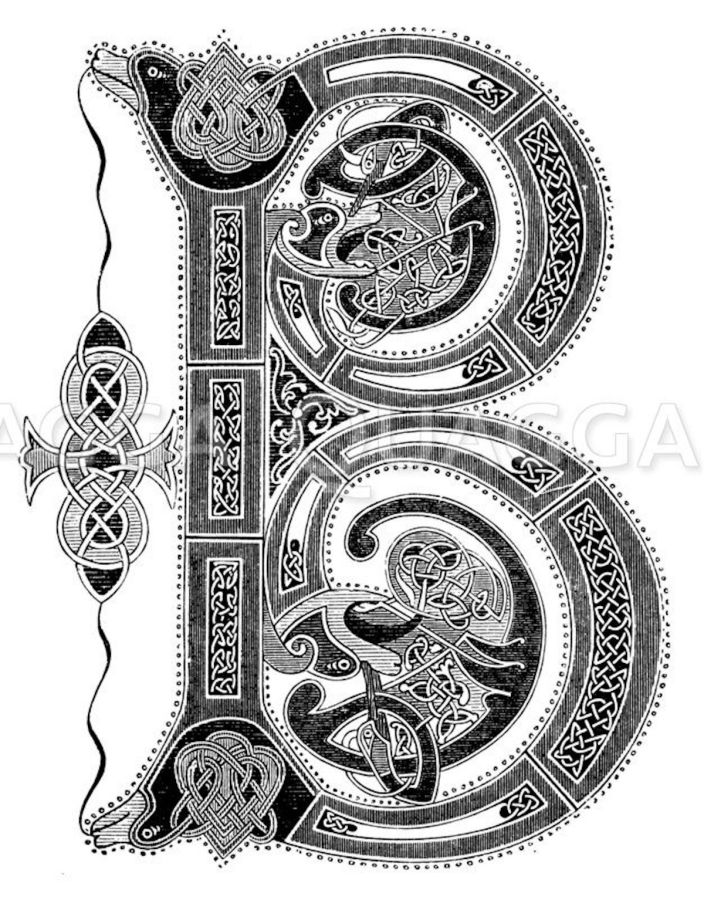
Von der Feder bis zum Bleisatz - Schrift in ihrer schönsten Form: Visuelle Zeitreise durch die Typografie
Berlin, 19. August 2025 - Die renommierte Bildagentur Quagga Illustrations stellt als aktuelles Highlight eine außergewöhnliche Sammlung historischer Buchstaben-Abbildungen aus ihren Archiven vor.
Initiale B, Mitte des 9. Jahrhunderts (© Quagga Illustrations)(firmenpresse) - Die exklusive Kollektion umfasst hochwertige Reproduktionen typografischer Meisterwerke aus verschiedenen Epochen - von auf Stein, Leder oder Papyrus verewigten antiken Buchstaben über reich verschnörkelte Barockbuchstaben bis hin zu eleganten Jugendstil-Schriften:
"Buchstaben sind mehr als nur Schriftzeichen - sie sind Zeitzeugen", erklärt Isabel Meraner, Pressesprecherin von Quagga Illustrations. "Jede Epoche hat ihre eigene visuelle Sprache, auch für die Typografie, und diese Sammlung macht ihre Wandlungen erlebbar - gestochen scharf, brillant reproduziert und sofort einsetzbar für kreative Projekte."
Die Motive stammen aus historischen Büchern, Plakaten, Manuskripten und Druckwerken, einzeln digitalisiert, farbgetreu aufbereitet und mit detaillierten Metadaten versehen. Die Sammlung eignet sich ideal für Verlage, Grafikdesigner:innen, Museen, Werbeagenturen und Kulturinstitutionen, die ihren Projekten einen authentischen historischen Charakter verleihen möchten.
Besondere Highlights der Kollektion sind unter anderem:
- Buchstaben der ägyptischen, babylonischen, griechischen oder römischen Antike
- Initialen aus Werken der Renaissance und des Barock
- Typografische Ornamente des Jugendstils
- Experimentelle Lettern aus den 1920er-Jahren im Bauhaus-Stil
- Verspielte Reklameschriften, Symbole und Vignetten der Gründerzeit
Von der Feder bis zum Bleisatz - Schrift in ihrer schönsten Form.